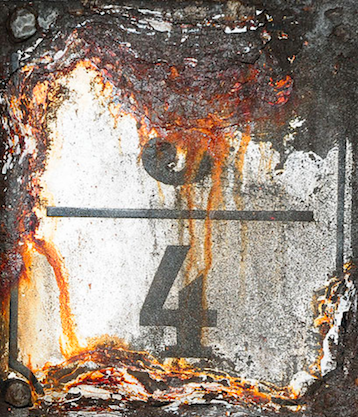
Frage nach der vewendeten Schriftart bei der Kilometrierung
Liebes Forum, ich bin Modellbauer und errichte derzeit das Modell eines zwischen 1880 und 1890 erstellten Eisenbahntunnels. Dieser weist im Original eine Kilometrierung auf Emaillieschildern auf, von denen noch wenige lesbare exisieren und von denen ich drei Muster beigefügt habe.
Kann mir jemand sagen, welche Schriftart verwendet wurde? Die Schilder könnten auch erst später angebracht worden sein.
Die Schrift bzw. Schriften der Emaileschilder wird sich wahrscheinlich nicht finden lassen – das waren sicher Schablonen eines kleinen Herstellers. Es gibt aber diverse Schriften die in diese Richtung gehen. Spontan fallen mir Numbers IndiciaHenriette und Clarendon ein. Alles »nur« ähnlich aber als Ausgangspunkt sicher hilfreich. Von den besagten Schriften könnte ich dir Zahlen absetzen und als PDF schicken.